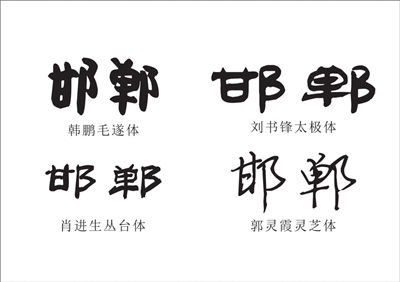
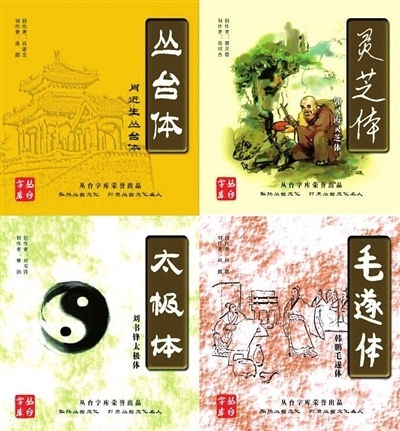
《丛台字库》
“我手机里设定的字体就是邯郸‘毛遂体’,大家都说这字体灵活多变、憨态可掬,可我怎么也没想到这个字体创始人竟是18岁的邯郸小伙儿!”日前,中国字体字库筹委会主席、徐悲鸿纪念馆国画室执行主任梁秋生专程从北京赶到我市丛台区文化创意园,对《丛台字库》进行考察调研。
梁秋生一行实地查看了《丛台字库》中的“灵芝体”、“毛遂体”、“太极体”和刚刚网站上线的“丛台体”,并与该字库创始人韩绍杰、“毛遂体”创始人韩鹏进行交流探讨。“字库里的四款字体各有特色,但中心思想都是围绕着邯郸历史典故而创建,与邯郸独特的成语文化一脉相承。”梁秋生深有感触地说。目前“丛台体”虽然已经在中国字库网、华夏字库成功上线发布,但手机APP客户端还未正式上线。梁秋生表示,回去以后他会积极协调字体管家软件,争取早日把“丛台体”推向手机APP客户端,让“丛台体”实现网站与手机的无缝链接。
据《丛台字库》创始人韩绍杰介绍,《丛台字库》于2013年6月正式成立,陆续收录“灵芝体”、“毛遂体”、“太极体”、“丛台体”,这四款电脑字体都是严格按照国家语言文字委员会字体字库标准设置,每套字体共录入6763个汉字,完全能够满足网民及各种传媒日常应用。韩绍杰自豪地告诉记者:“我们《丛台字库》里的字体,不论是网站还是手机APP客户端都可以免费下载、安装和使用。不图别的,就是为了方便全球华人了解邯郸历史,在网络上弘扬邯郸文化!”(记者郭晓月 通讯员吴超)